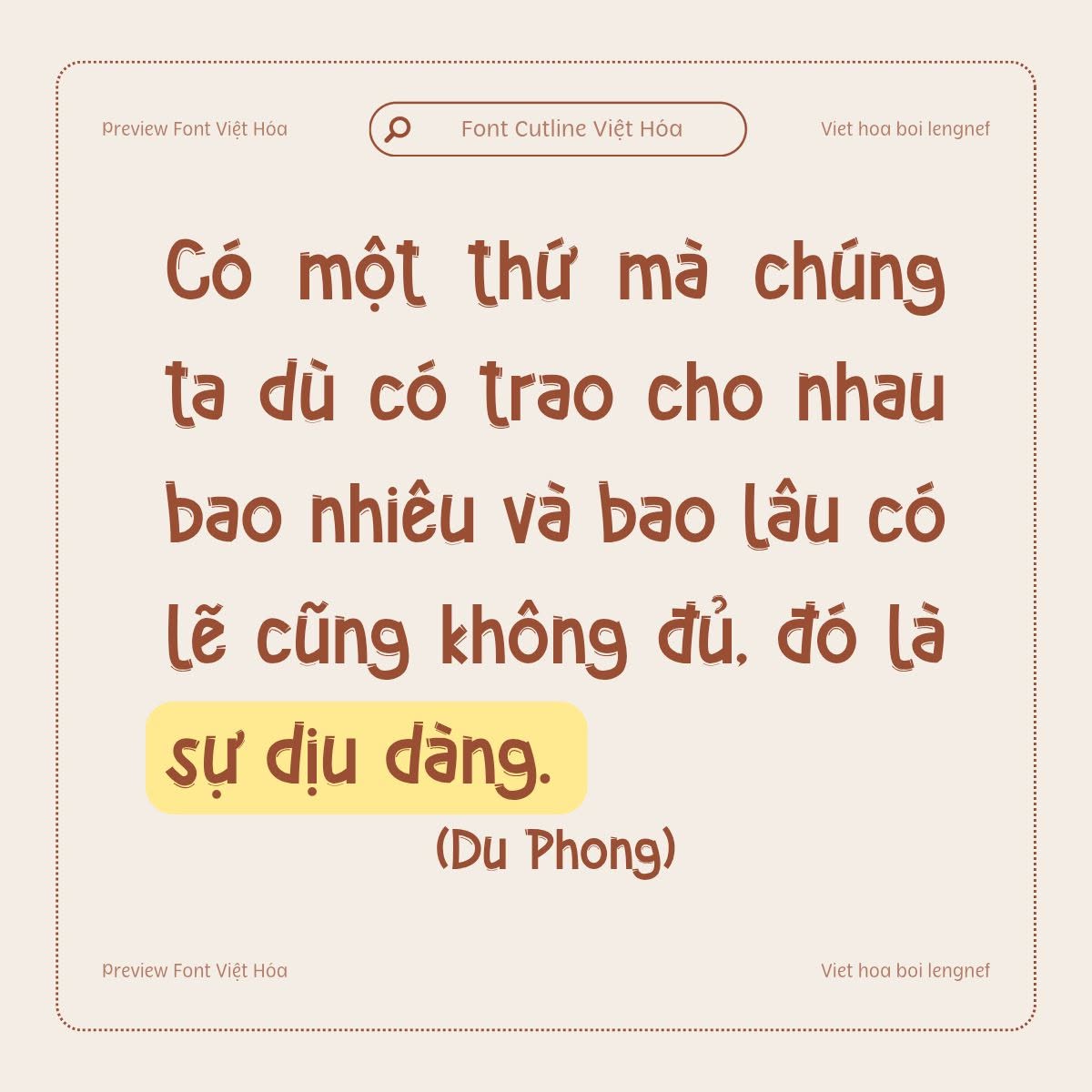
Việt hóa theo yêu cầu 19 || LF Cutline
• Tác giả: BrandSemut
• Việt hóa: lengnef
Font LF Cutline Việt hóa
Cutline là một phông chữ viết tay dễ thương, vui nhộn và ngọt ngào. Phông chữ này phù hợp cho tất cả các dự án DIY thủ công, logo, thương hiệu, mạng xã hội, v.v.